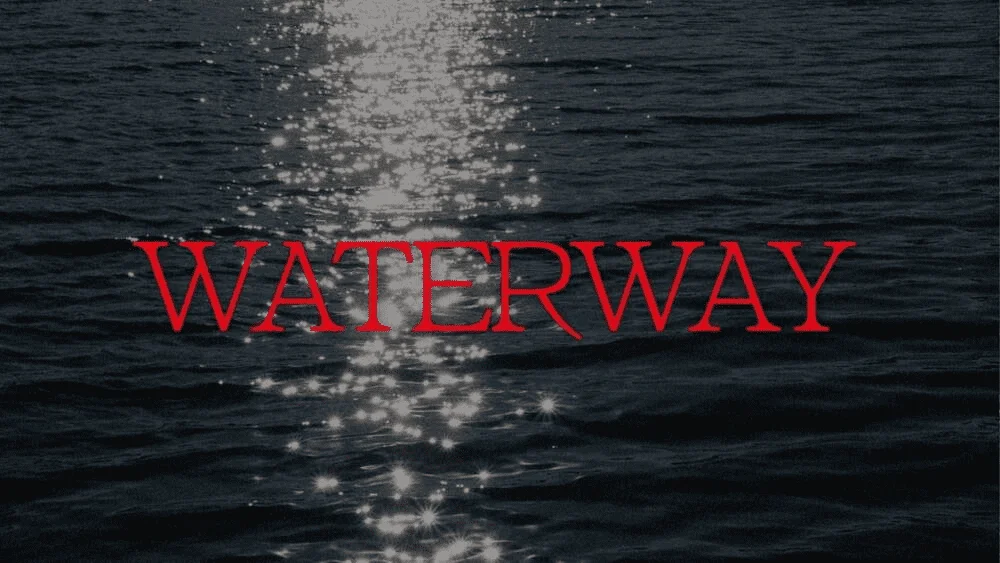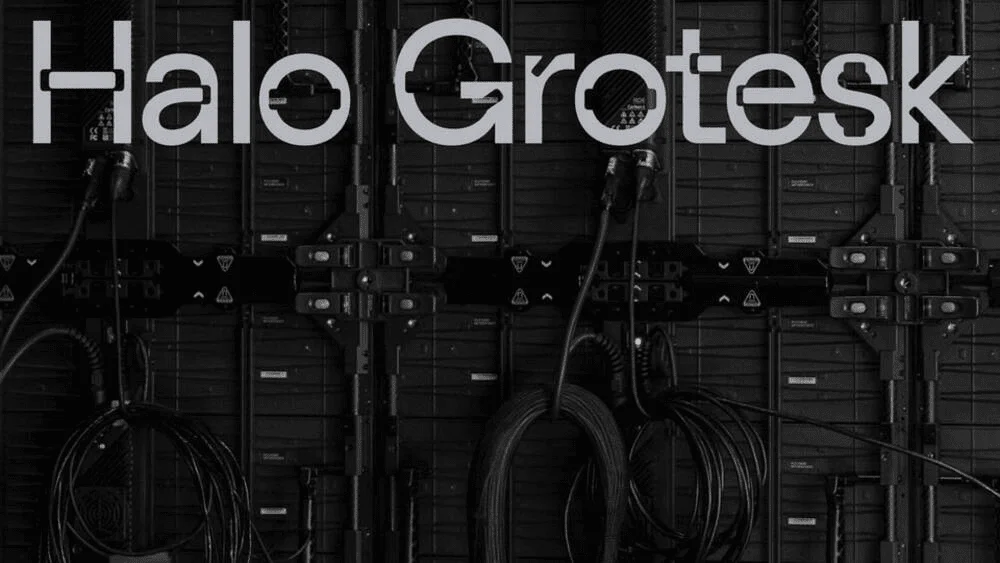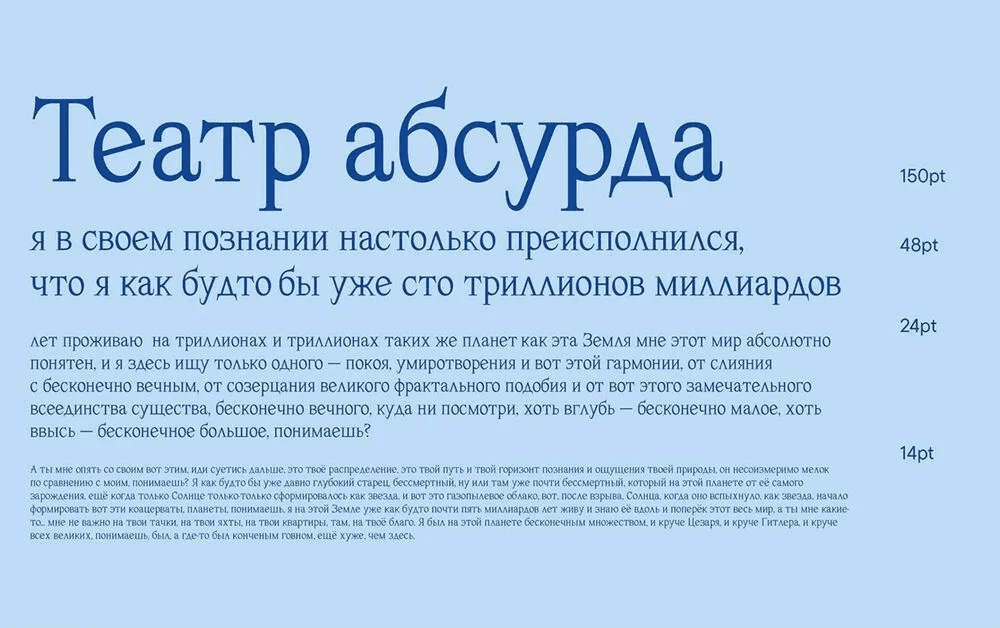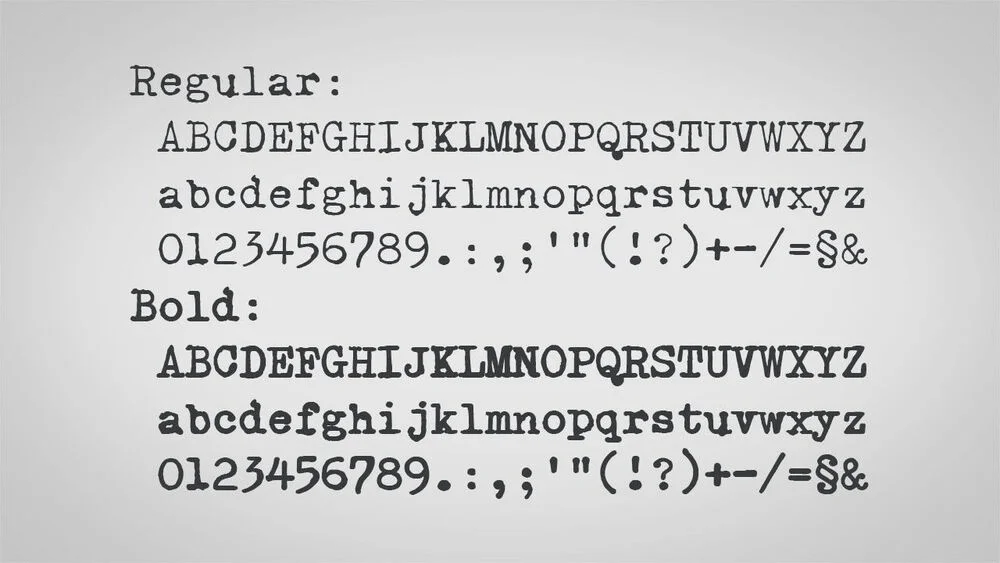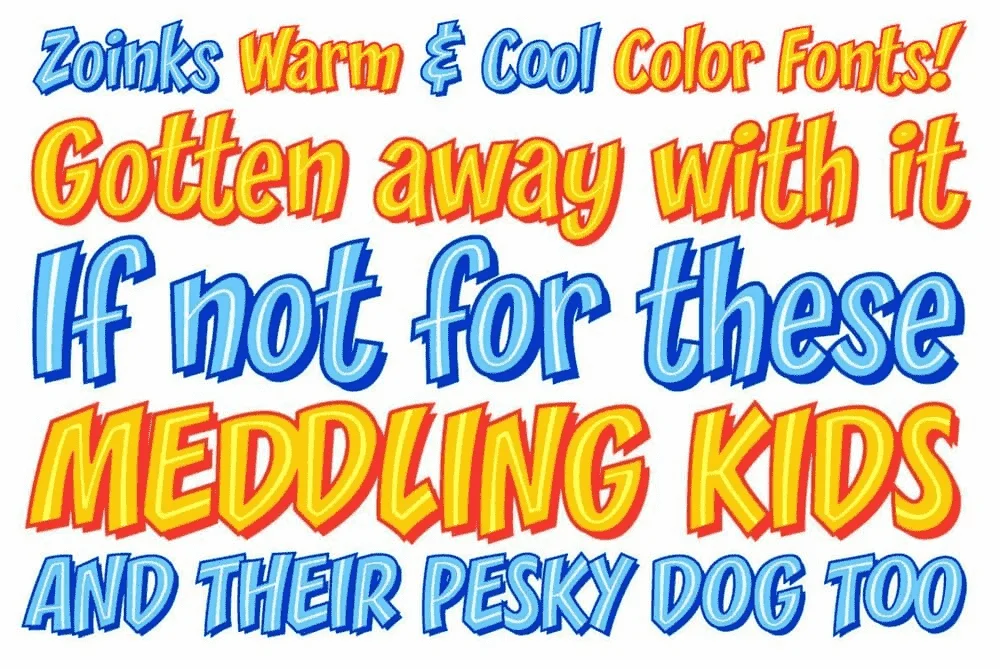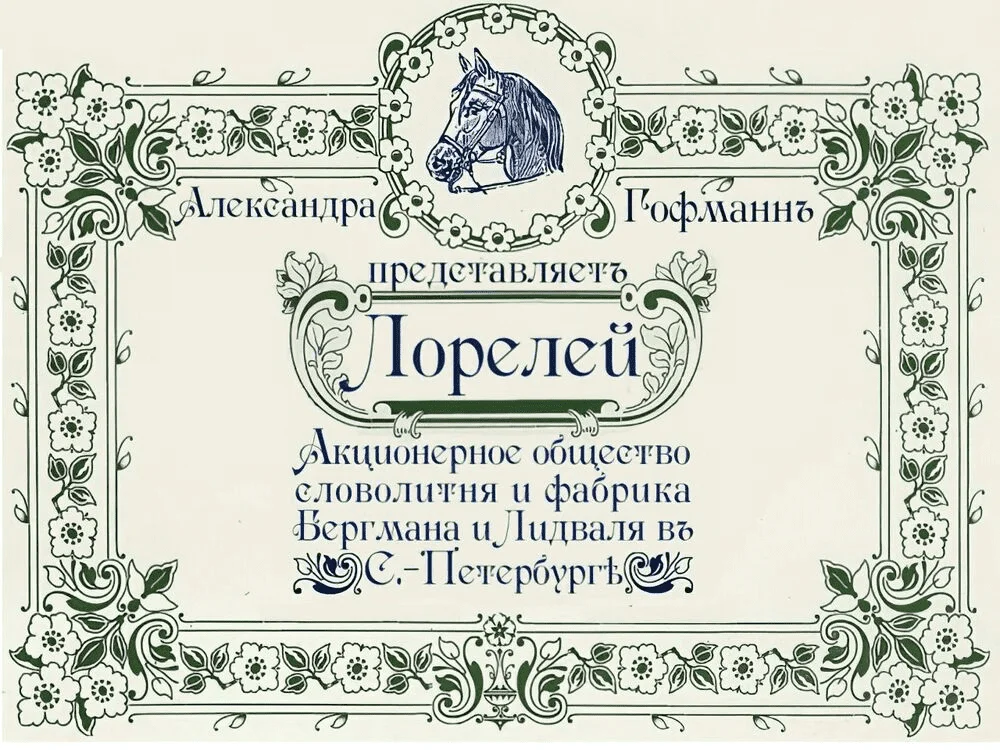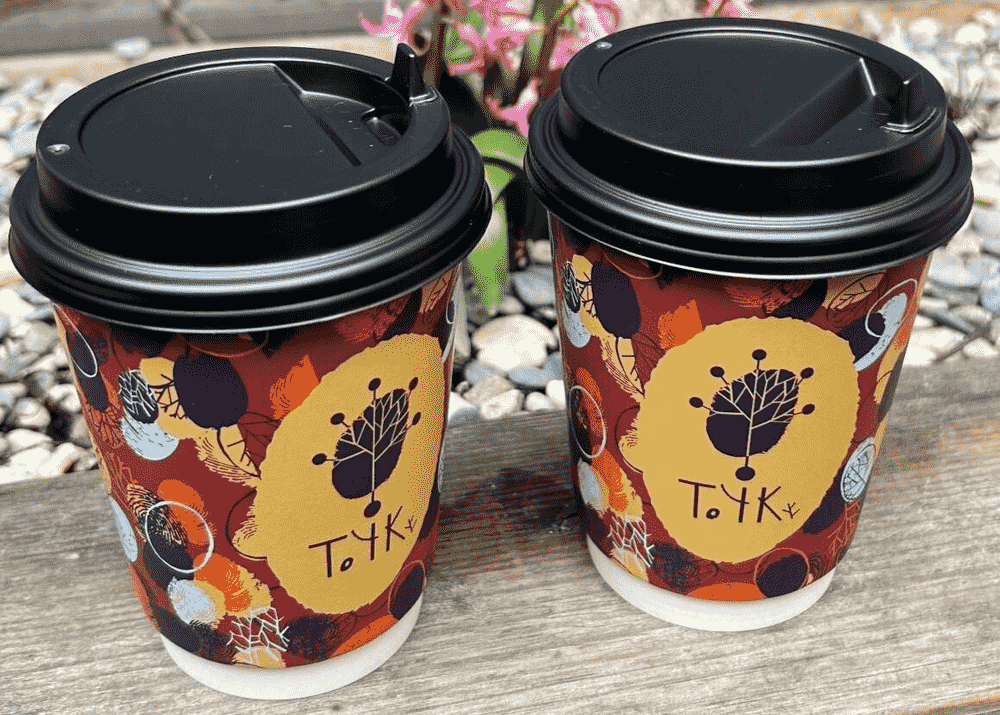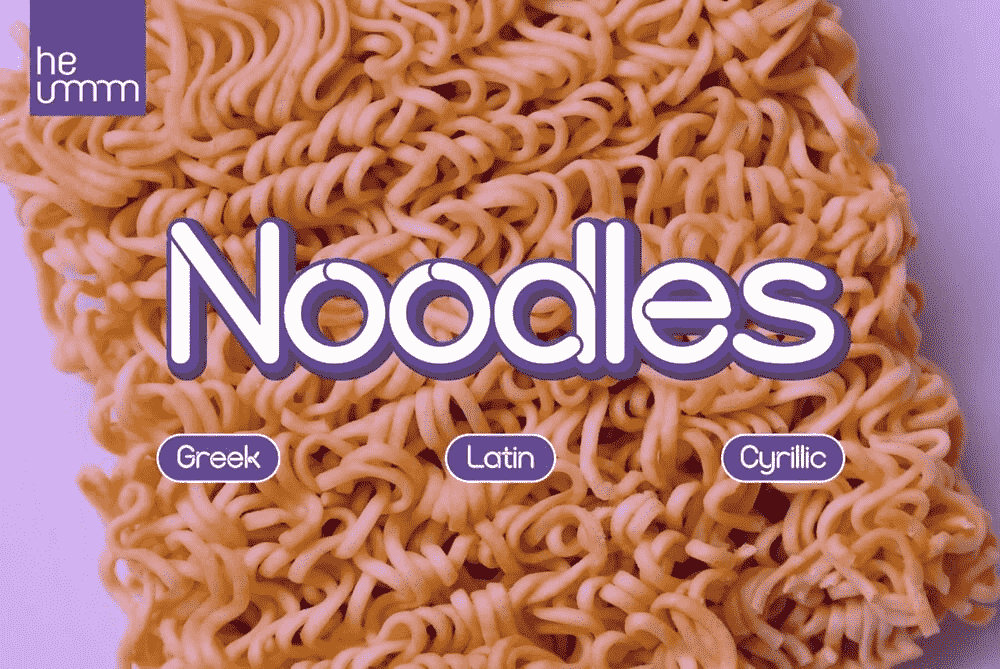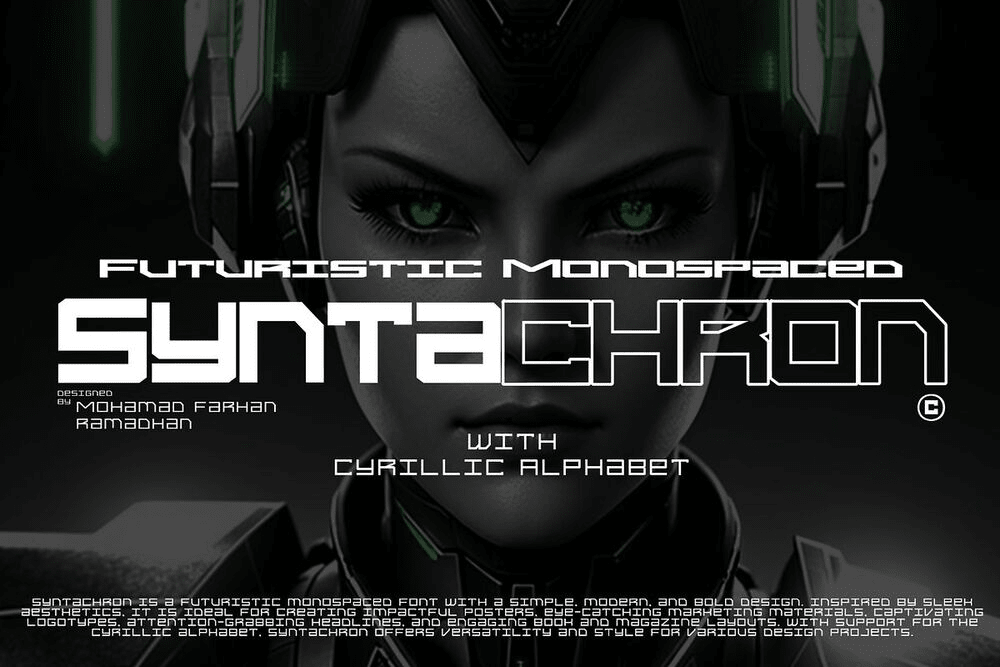
Шрифт логотипа формирует первое впечатление о бренде. Важно, чтобы он отражал его особенности и был запоминающимся. Но найти оригинальный вариант с поддержкой кириллицы — задача не из простых. Чтобы ускорить поиски, собрали подборку из 15 трендовых шрифтов и советы, как их сочетать.
| Для технологических компаний | Robloxian, Halo Grotesk, Syntachron |
| Для творческих проектов | CC Zoinks, Loreley Antiqua, Kurochka Lapkoi, HUNoodles, Waterway, ST-Artefakt, Absurdite, X Typewriter, Stoneberry |
| Универсальные | Bounded, Nuqun, Uncage |
Шрифт для логотипа должен быть не только эстетичным, но и функциональным. Чтобы подобрать подходящий вариант, ориентируйтесь на базовые параметры:
Соответствие концепции. Выбирайте шрифт с учетом сферы деятельности и характера бренда. Подумайте, какие эмоции и ассоциации должны возникать у клиентов, когда они смотрят на ваше лого. Строгий гротеск, например, вызывает ощущение надежности и подходит банкам. Рукописные шрифты передают уют, дружелюбие и творческий дух, поэтому органично вписываются в логотипы кафе и арт-студий.
Визуальная гармония. Если в лого используются другие графические элементы, текст должен с ними сочетаться. Например, геометрические иконки хорошо смотрятся с гротесками. А контурные рисунки — с рукописными буквами.
Уникальность. Ищите свежие гарнитуры с запоминающимися деталями: необычными пропорциями, выразительным контрастом или нестандартными формами букв. Отдавайте предпочтение гарнитурам, которые появились на рынке 2–3 года назад. Они реже встречаются у конкурентов и выглядят современнее.
Читабельность. Убедитесь, что название компании считывается без труда. Избегайте гарнитур с тонкими линиями, перегруженным декором и слишком похожими друг на друга буквами. Например, есть шрифты, в которых легко спутать «З» и «Э», «Л» и «П».
Адаптивность. Логотип должен смотреться одинаково хорошо на разных носителях — на сайте, вывеске, сувенирной продукции. Для международных брендов важно, чтобы шрифт поддерживал и кириллицу, и латиницу. Это позволит локализовать лого для разных рынков.
Шрифт Bounded — современная версия популярного Unbounded, разработанная Владом Чуркиным. Благодаря четким линиям и отсутствию засечек выглядит сдержанно и внушает чувство стабильности. Она универсальна и подходит как страховым компаниям, которые стремятся завоевать доверие клиентов, так и креативным агентствам, которым важна лаконичная, но выразительная типографика.
Nuqun — шрифт без засечек с мягкими геометричными линиями. В нем сочетаются четкость гротеска и легкость рукописного стиля. Такой баланс делает шрифт удобочитаемым и гибким в использовании. Он смотрится уместно как в логотипах финансовых и консалтинговых компаний, так и брендов lifestyle-сегмента.
CC Zoinks — декоративный шрифт студии Comicraft. Небольшой наклон, асимметрия и диагональные срезы придают ему мультяшный характер. Гарнитура подходит компаниям, которые выпускают продукцию для детей — например, одежду или игрушки.
Винтажный шрифт с засечками Loreley Antiqua придумала Александра Гофманн в 2022 году. Плавные линии, классические пропорции и изящные завитки подчеркивают его ретро-шарм. Гарнитура удачно впишется в айдентику исторических проектов и брендов с ностальгической атмосферой. Например, антикварных магазинов и винодельческих домов.
Рукописный шрифт Kurochka Lapkoi был придуман за один день. Его отличает легкая небрежность: наклон влево, неровные линии и разная высота букв. Гарнитуру можно использовать в лого творческих студий и крафтовых проектов — например, домашних кондитерских и магазинов подарков ручной работы.
Геометрический шрифт Robloxian создан на основе Gill Sans Nova Ultra Bold и вдохновлен логотипом игровой платформы Roblox. Для него характерны прямые линии и широкие буквы. Гарнитура органично смотрится в логотипах IT-компаний, которые занимаются геймдевом и разрабатывают мобильные приложения для молодежной аудитории.
Буквы в шрифте HUNoodles закручены, как спагетти, поэтому логотипы с ним выглядят аппетитно. Гарнитура подходит брендам, которые производят пасту, и гастрономическим проектам — например, ресторанам итальянской и азиатской кухни. Также может подойти для цифровых продуктов, мероприятий или сферы розничной торговли: несмотря на название, прямых ассоциаций с лапшой пластика букв не вызывает.
Uncage — универсальный гротеск, разработанный Владимиром Кленовым. Шрифт основан на чистых геометрических формах, что делает его лаконичным и легко читаемым на любых носителях. Гарнитура подходит брендам, которые придерживаются эстетики минимализма. Хорошо смотрится в логотипах технологических компаний и e-commerce-платформ.
Обычно для логотипа достаточно одного шрифта. Если же хочется сочетать несколько, ограничьтесь двумя, максимум — тремя, чтобы не перегружать композицию. Важно, чтобы шрифты гармонировали между собой. Если один из них выразительный, другой должен быть более нейтральным. Можно поиграть с разными начертаниями внутри одной гарнитуры. Например, комбинировать обычное и полужирное. Если хотите больше идей по сочетаниям, читайте наш гайд по подбору шрифтовых пар.